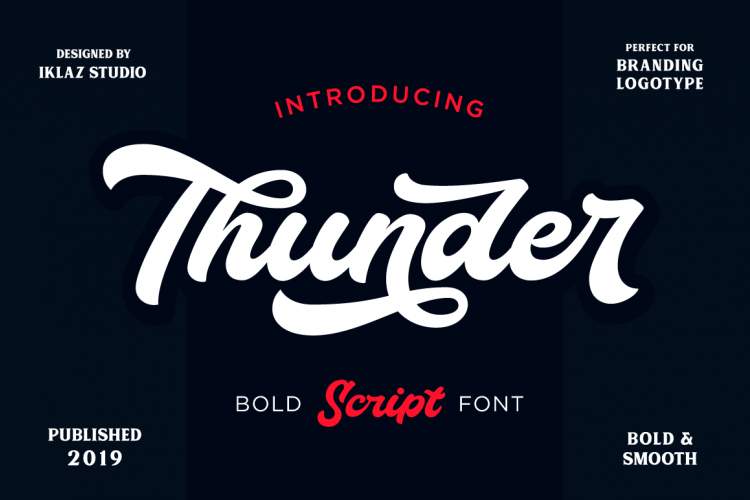
Thunder Bold Script Font – Download Grátis
Esta font Thunder Bold Script é uma mistura única de elegância moderna e movimento círculo, criada para dar vida ao seu design de forma instantânea. Foi projetada pelo talentoso designer Iklaz Studio. Composta para facilitar o processo de criação de letras a mão, esta fonte oferece um estilo firme e suave, perfeita para projetos como logotipos, branding, embalagens, artigos de consumo, etiquetas e muito mais. Ela é uma escolha incrível se você está buscando dar um toque único e vibrante a seus trabalhos gráficos, seja em pequenas criações ou maiores projetos. Experimente Thunder Bold Script e transforme suas ideias em algo extraordinário.